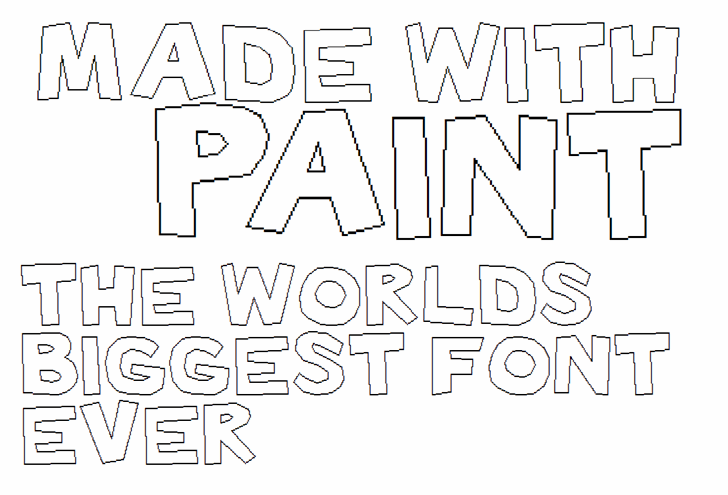
Made with Paint font – Download Grátis
A Made with Paint font é uma criação inédita e vibrante que surge do universo criativo da FontStruct. Em 2015, o designer Daniel Lyons (comumente conhecido como 538Lyons) teve a ideia de desafiar os artistas digitais ao criar um grande fonte diretamente no FontSpace, usando apenas a ferramenta gratuita Paint. Esta fonte é uma obra-prima de ingenuidade e criatividade, resultado direto da técnica manual de construir fontes do FontStruct. A Made with Paint foi feita por 538Fonts em parceria com o Designer Hamilton. Ela traz um ar exuberante e vibrante que faz dela uma escolha perfeita para qualquer projeto gráfico, seja ele uma arte digital sofisticada ou uma expressão artística mais descontraída. É perfeitamente adequada para uso em aplicações visuais de todos os tipos – desde design editorial e letras gigantes até logotipos e mensagens digitais. A fonte é um testemunho da capacidade humana de transformar simples ferramentas e ideias em algo realmente único e poderoso.